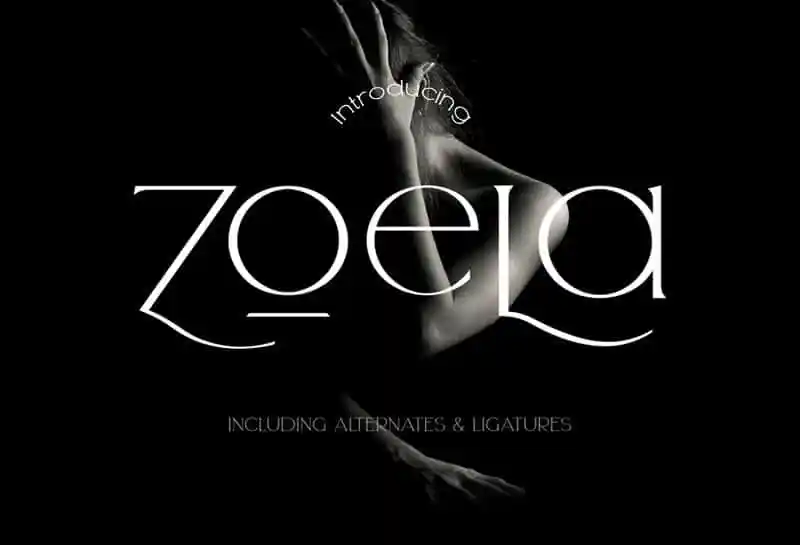
Zoela Serif Font é uma elegante escolha para projetos que requerem destaque visual através do uso de serif. Com cada letra cuidadosamente criada, essa fonte moderna cria textos únicos e memoráveis. Desenvolvida pela Dxsign em 99designs, Zoela oferece um estilo sofisticado ideal para aplicativos visuais como capas de revistas ou títulos grandiosos. O design multilíngue inclui alternativas de letras, números e pontuação que permitem maior versatilidade. Além disso, a fonte apresenta um estilo regular além do popular display style, garantindo uma diversidade para atender às necessidades específicas dos projetos. Para aqueles buscando criar texturas personalizadas, Zoela Serif Font é perfeita para qualquer empreendimento que exija um touch único e sofisticado.